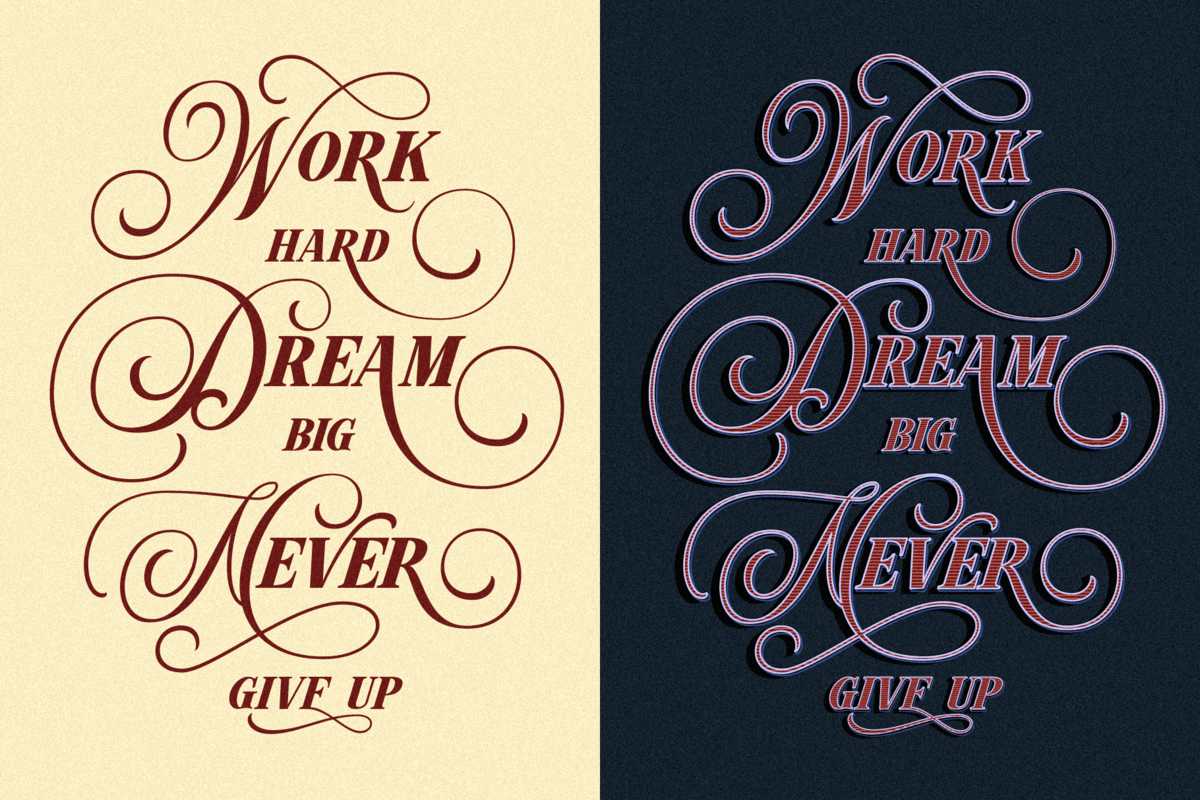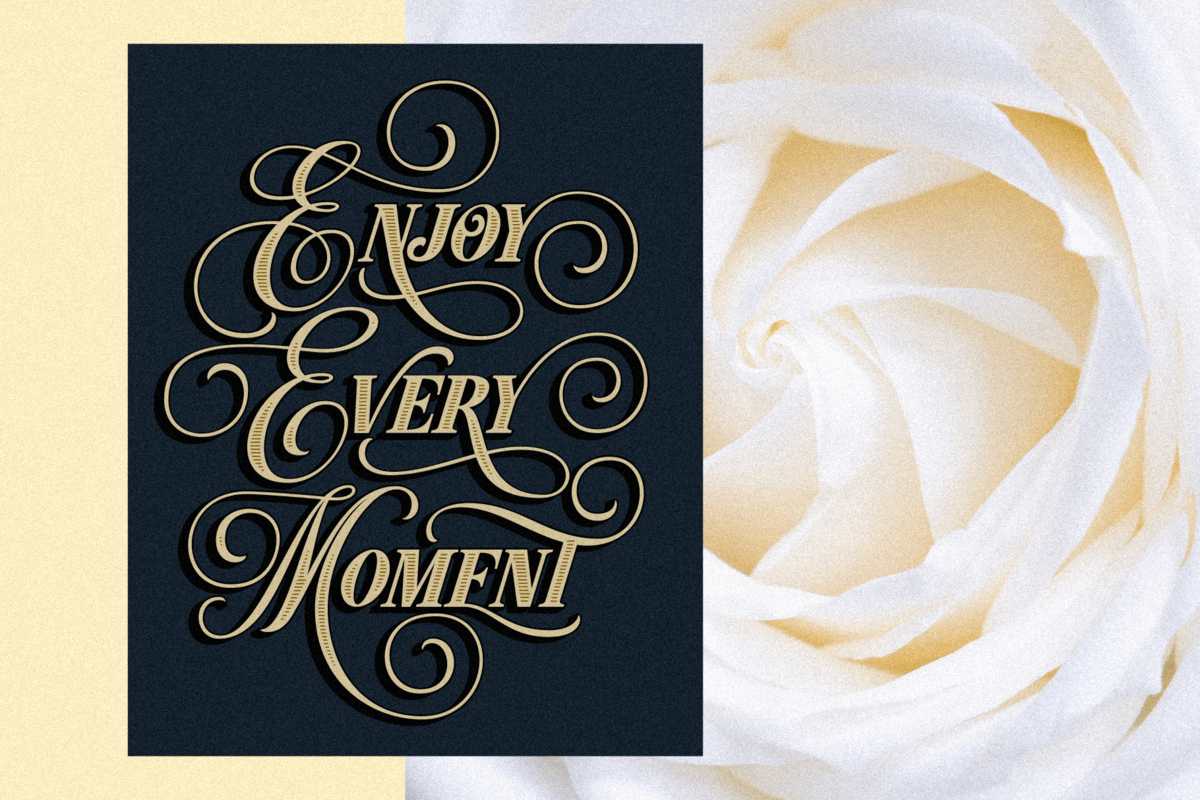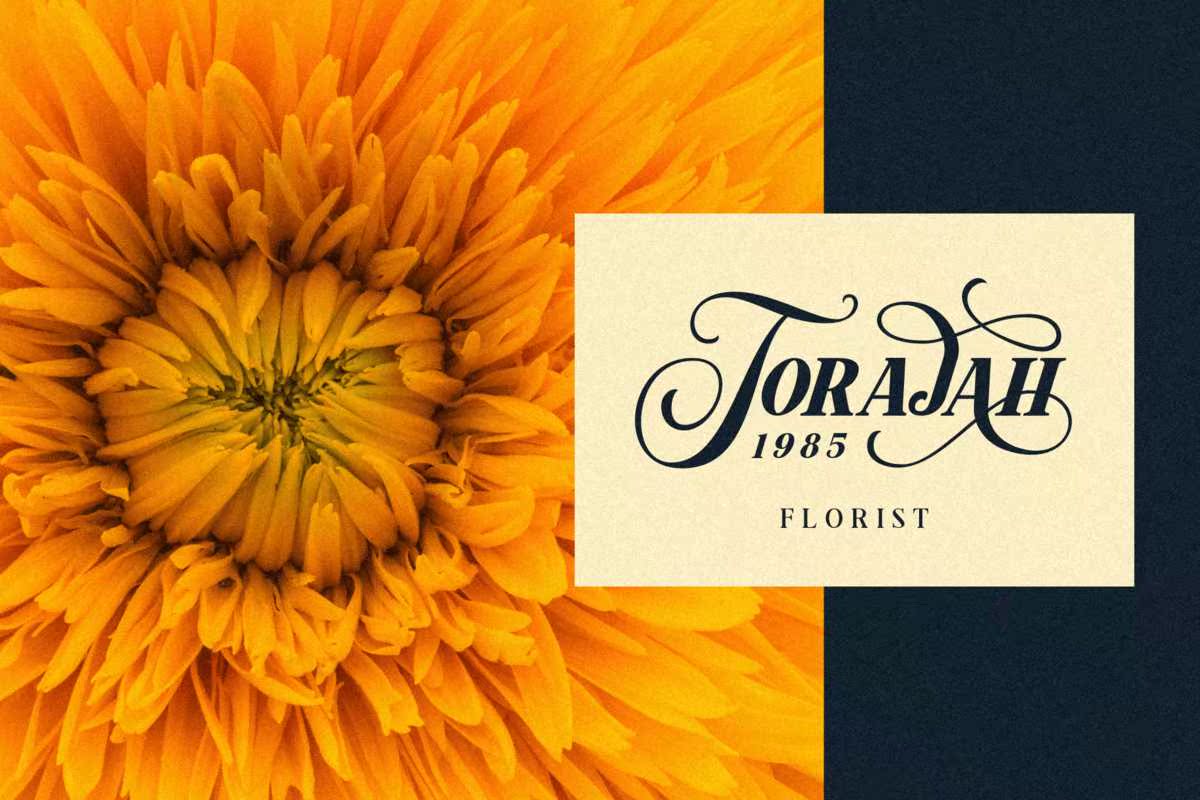
介绍Hondurhas,一个结合了脚本大写框和花框的新概念,用于显示目的。出现了许多可播放的替代品,因此您可以根据自己的需要混合使用。仍然不够好吗?Hondurhas还可能出现分层系统。07FONTSTOTAL!。因为我们相信,层数越多就越有趣。事实上,这种字体非常适合你的许多设计项目,如传单、标志设计、徽章、包装、邀请等等。介绍Hondurhas,这是一种新概念,它结合了脚本外壳和花格,用于显示目的。出现了许多可播放的替代品,所以你可以满足你的需要。还不够好吗?洪都拉斯也有分层系统。07FONTSTOTAL!。因为我们相信,更多的层次更有趣。事实上,这是你许多设计项目的完美选择,如传单、标志设计、徽章、包装、邀请等等。